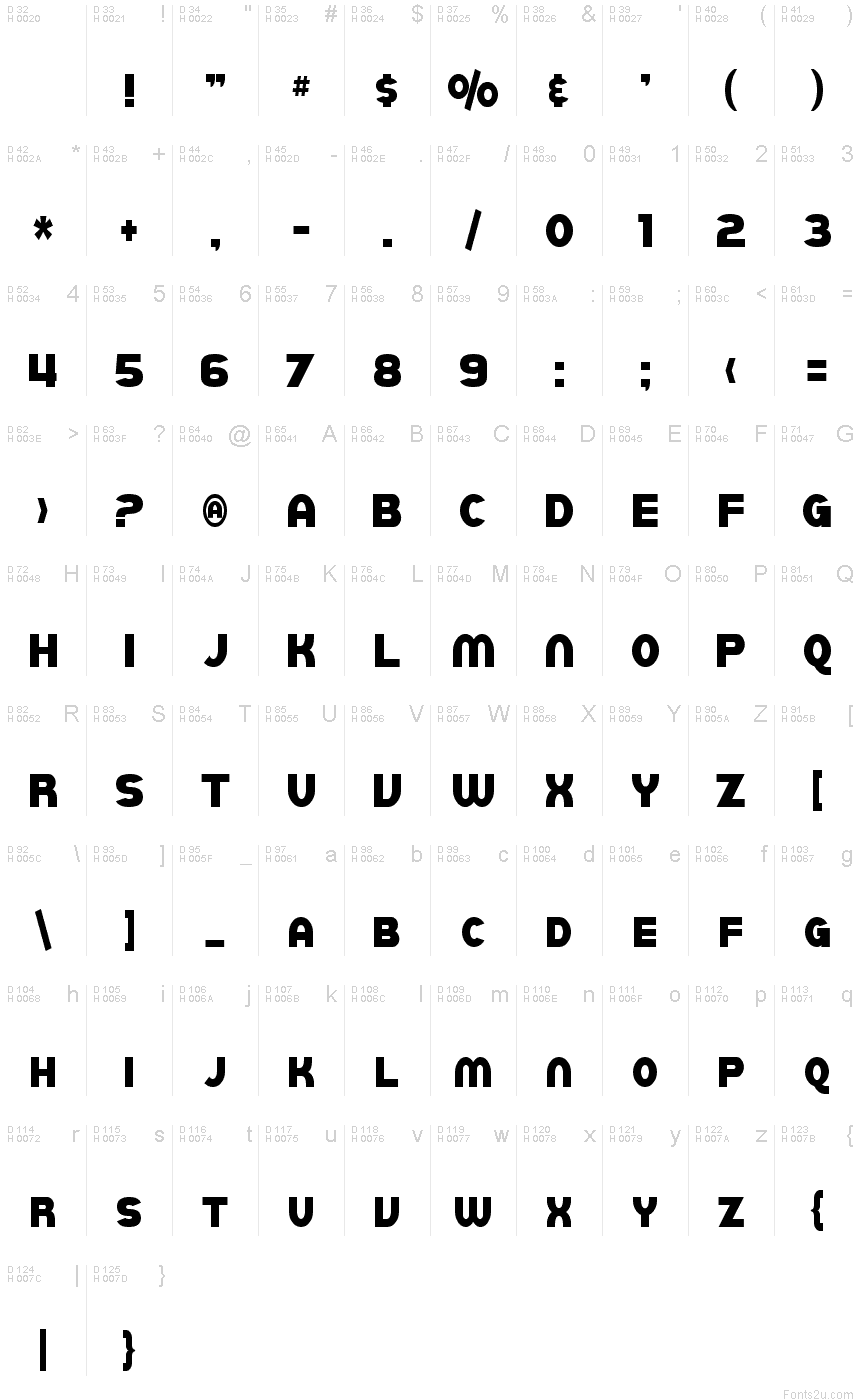
SF Juggernaut Condensed od ShyFoundry to nowoczesny, darmowy krój typu display o ciężkiej, skondensowanej budowie i gładkich, niemal rzeźbiarskich krzywiznach. Litery sprawiają wrażenie masywnych, ale nie sztywnych, dzięki szerokim formom, ściętym łączeniom i zaokrąglonym rogom, które nadają alfabetowi surowy, muskularny rytm.
Świetnie sprawdzi się w nagłówkach plakatów, logo gier, na okładkach i w brandingu sportowym, gdzie wąskie wielkie litery pozwalają nadać krótkim słowom wyrazistego charakteru. Jako darmowy font idealnie nadaje się też na ulotki i grafiki reklamowe (merch), zwłaszcza jeśli szukasz głośnego, kompaktowego znaku z nutką retro-futuryzmu.
SF Juggernaut Condensed
ShyFoundry
Derek Vogelpohl